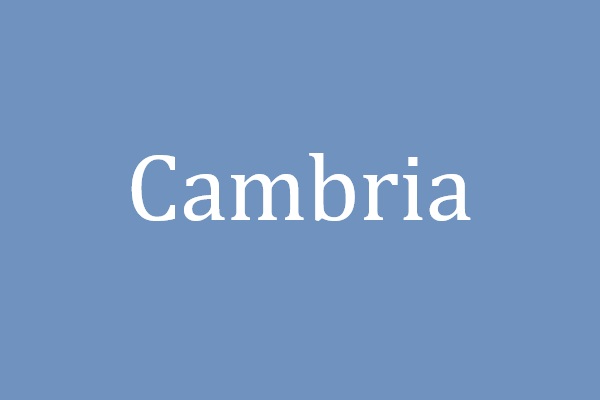
Nhu cầu tìm và cài đặt font Cambria việt hóa vẫn khá phổ biến, đặc biệt với sinh viên, giảng viên và dân văn phòng thường xuyên làm việc với luận văn hoặc báo cáo dài. Trong bài viết này, Xưởng In Viva chia sẻ bộ font cambria việt hóa đầy đủ để bạn sử dụng thuận tiện trong Word, PowerPoint và nhiều loại tài liệu khác nhé!
Font chữ Cambria được tạo ra để phục vụ việc soạn thảo văn bản dài. Vì vậy khi download cambria font, người dùng thường sử dụng cho báo cáo, luận văn hoặc tài liệu nghiên cứu.
Thuộc tính Thông tin
Tên font Cambria
Kiểu chữ Serif
Nhà phát triển Microsoft
Ứng dụng Tài liệu học thuật, báo cáo
Khi download font cambria, bạn sẽ nhận được nhiều biến thể khác nhau như Regular, Bold hoặc Italic để phục vụ việc trình bày nội dung trong tài liệu.
Font Cambria là gì?
Cambria là font serif được Microsoft phát triển cùng thời với Calibri khi bộ Microsoft Office 2007 ra mắt. Trong đó, Calibri thường dùng cho văn bản thông thường, còn Cambria được tối ưu cho các tài liệu dài và nội dung học thuật.
Điểm nổi bật của Cambria là các nét chữ có chân (serif) rõ ràng, giúp mắt dễ theo dõi từng dòng khi đọc đoạn văn dài. Điều này đặc biệt hữu ích với các tài liệu nhiều trang như luận văn, bài nghiên cứu hoặc sách điện tử.
Font Cambria được sử dụng rộng rãi trong môi trường học thuật và văn phòng nhờ nhiều ưu điểm về khả năng hiển thị và tính ổn định. Đây cũng là lý do nhiều người vẫn tìm cambria download font khi làm việc với tài liệu dài.
• Dễ đọc khi in: cấu trúc chữ rõ ràng giúp tài liệu in ra giấy dễ đọc hơn.
• Nét chữ cân đối: khoảng cách giữa các ký tự hợp lý giúp văn bản không bị rối.
• Phong cách serif cổ điển: tạo cảm giác trang trọng và chuyên nghiệp cho tài liệu.
• Phù hợp cho tài liệu học thuật: thường được dùng trong luận văn, báo cáo nghiên cứu hoặc sách điện tử.
• Nhiều biến thể chữ: hỗ trợ Regular, Bold, Italic và Bold Italic để trình bày nội dung linh hoạt.
Nhờ những đặc điểm này, nhiều người lựa chọn font cambria việt hóa để soạn thảo tài liệu học thuật hoặc báo cáo dài.
Các kiểu chữ trong bộ font Cambria
Khi download font cambria, bạn sẽ nhận được nhiều kiểu chữ khác nhau trong cùng một bộ font. Những biến thể này giúp người dùng trình bày nội dung khoa học hơn mà vẫn giữ sự đồng bộ trong toàn bộ tài liệu.
• Cambria Regular
• Cambria Bold
• Cambria Italic
• Cambria Bold Italic
• Cambria Math
Đặc biệt, nhiều người tìm cambria math font download hoặc download cambria math font vì font này được dùng để hiển thị công thức toán học trong Microsoft Word.
Ứng dụng khi sử dụng font Cambria trong thực tế
Nhờ khả năng hiển thị rõ ràng và bố cục cân đối, Cambria được sử dụng khá rộng rãi trong nhiều loại tài liệu khác nhau. Đặc biệt, khi cần soạn thảo văn bản dài, việc download cambria font sẽ giúp nội dung dễ đọc và chuyên nghiệp hơn.
Một số ứng dụng phổ biến của font cambria việt hóa gồm:
• Luận văn và báo cáo học thuật
• Tài liệu nghiên cứu
• Sách điện tử (ebook)
• Bài nghiên cứu khoa học
• Tài liệu Word nhiều trang
• Tài liệu in ấn
Nhờ khả năng đọc tốt trên cả màn hình và bản in, download font cambria là lựa chọn phổ biến trong môi trường học thuật.
Mẫu font chữ cambria dễ đọc
Mặc dù Cambria là font phổ biến, nhưng trong quá trình download font cambria, người dùng vẫn có thể gặp một số lỗi khiến tài liệu hiển thị không đúng.
• Font không hiển thị trong Word: do font chưa được cài đặt vào hệ thống.
• Thiếu ký tự tiếng Việt: xảy ra khi dùng phiên bản font chưa việt hóa.
• Chữ bị thay thế: máy tính không có font Cambria nên Word tự động thay bằng font khác.
• Lỗi công thức toán: thiếu font Cambria Math khi mở tài liệu có công thức.
Để tránh những lỗi này, bạn nên cài đặt đầy đủ bộ font cambria việt hóa bao gồm cả Cambria Math.
03 lưu ý khi sử dụng font Cambria
Mặc dù Cambria khá dễ sử dụng, nhưng để tài liệu hiển thị ổn định trên nhiều máy khác nhau, bạn nên lưu ý một số điểm quan trọng.
• Chọn đúng phiên bản font: tránh lỗi hiển thị khi mở file trên máy khác.